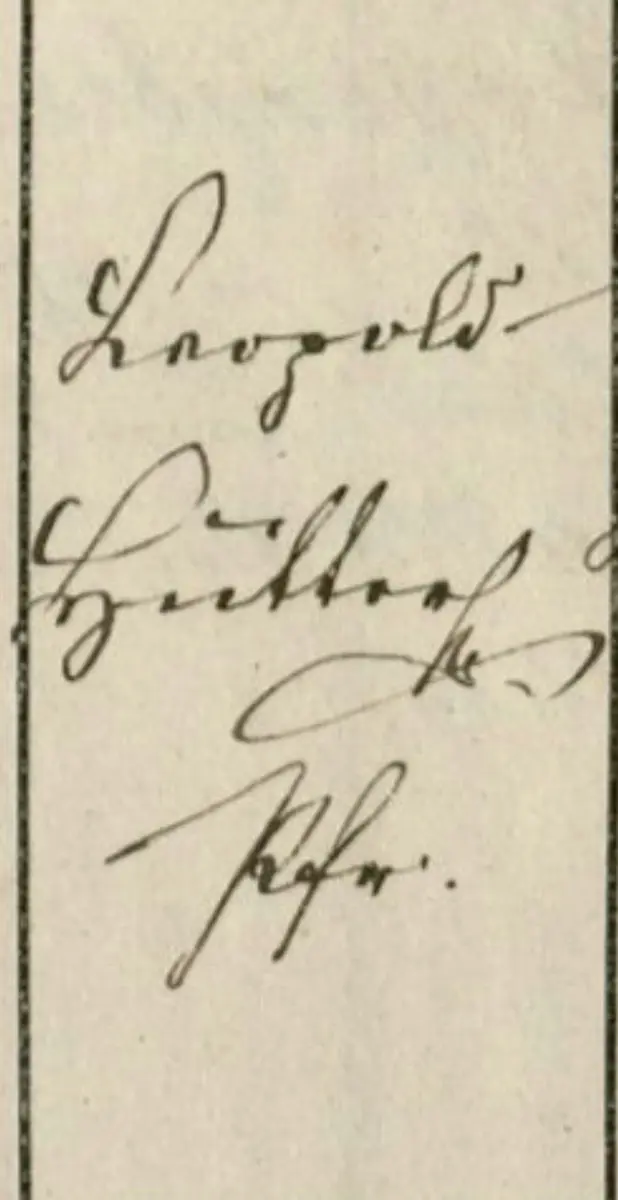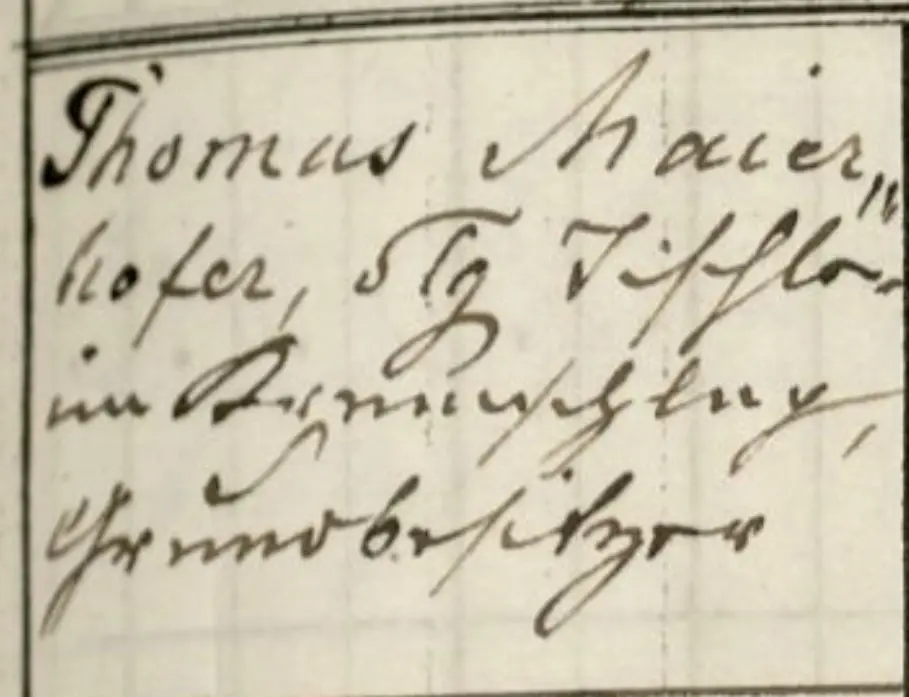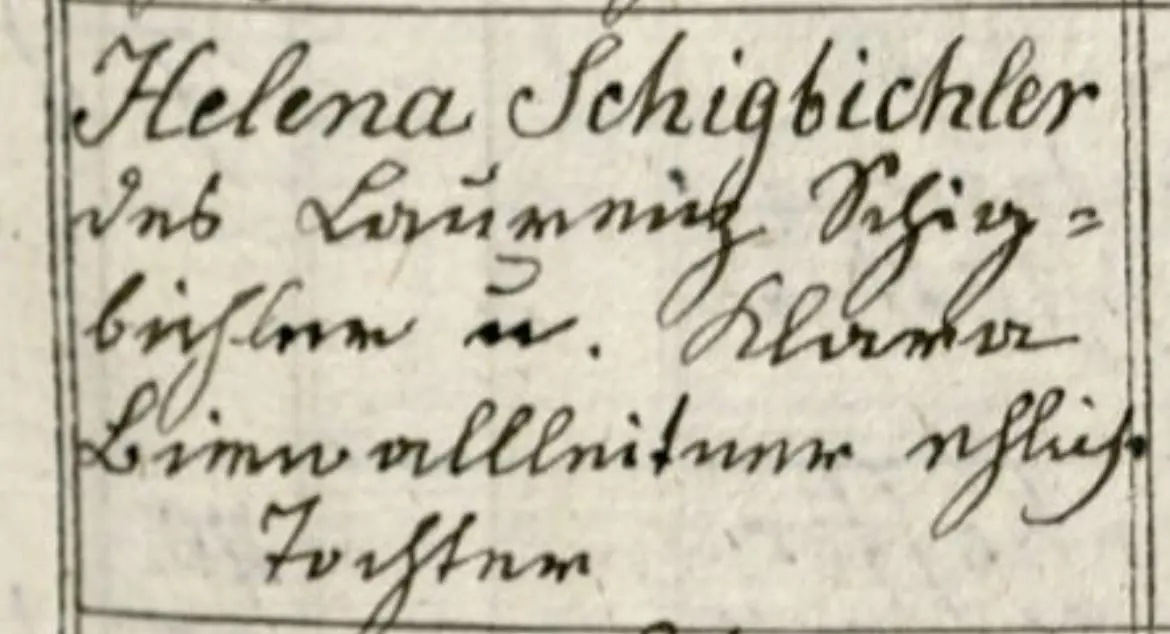
Stimmt. Könnte sein. Hab jetzt aber einige weiter schriftbeispiele gesehen. Es ist eher win grosses L und etwas nicht ganz definierbares. Kann das sein dass das eine paraphe ist? Ist dir sowas schon mal untergekommen?
Das „ogd“ könnte „vgo“ heissen… habe in einem anderen eintrag mit dieser handschrift dies so lesen können. Vgo würde für vulgo stehen und sinn machen
Drittes bild entziffert.
Mathilda Dampfhofer geprft (für geprüfte Hebamme) -
Ich glaub ich habs. Inwohnerin und Inwohner.